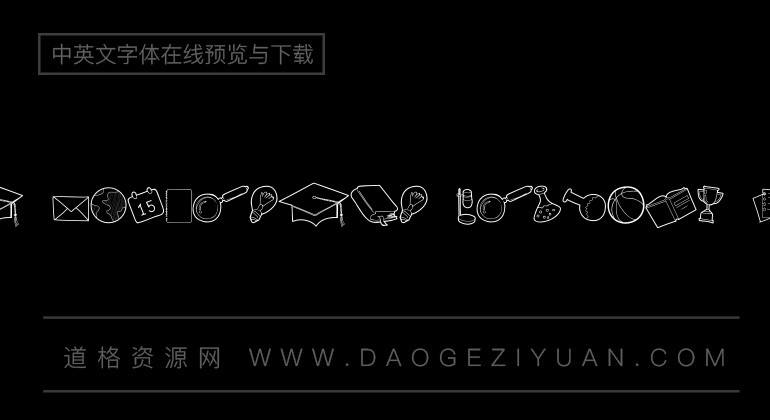
Kid Knowledge Clipart Font
Kid Knowledge Clipart Font 是一种具有卡通风格的字体,设计初衷是用于儿童相关的设计和教育资料。它的特点是拥有许多有趣的插图和符号,包括小动物、人物、天气、食物等,这些插图可以帮助儿童更好地理解和学习文本内容。 该字体包括了大写和小写字母、数字、标点符号以及许多特殊符号和插图,支持多种语言文字。它的颜色鲜艳、线条粗细适中,非常适合用于幼儿启蒙教育、儿童读物、教育海报等设计中。 Kid Knowledge Clipart Font 可以免费下载和使用,非常方便。不过需要注意的是,该字体仅适用于个人和非商业用途,如需商用需获得授权。
Kid Knowledge Clipart Font是一款非常不错的手写艺术字体,具有很好的视觉感,适合于文化类的宣传设计、商业类品牌的广告和产品包装设计以及个性化文字排版等较多场景。